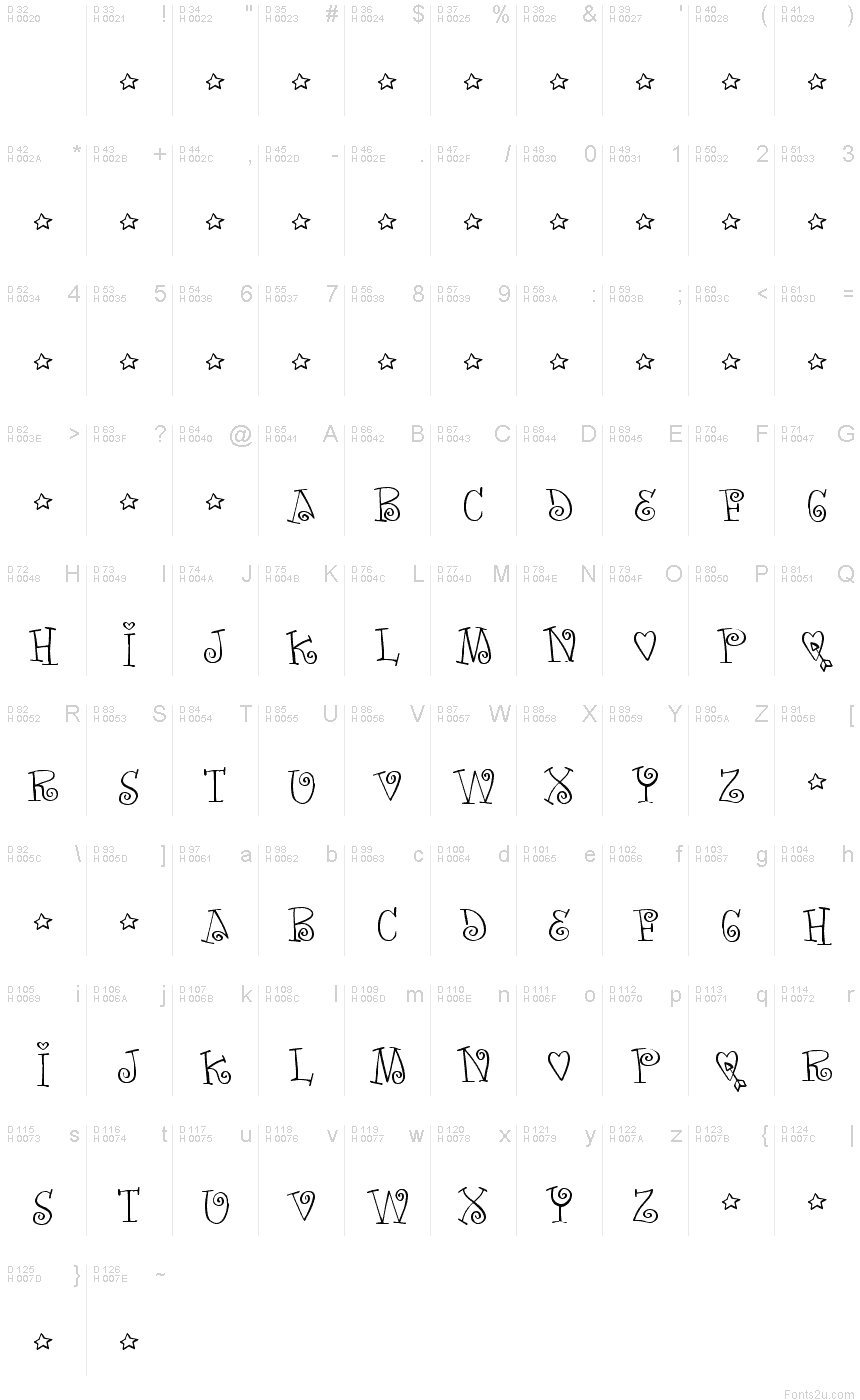
Words of Love autorstwa Jakoba Fischera to darmowy krój displayowy o romantycznym, popowym charakterze, wyglądający jak rysowany odręcznie. Wysokie, smukłe litery układają się w duże, spiralne pętle, a wplecione w zestaw motywy serc nadają krojowi słodkiego, lekko figlarnego uroku – bardziej w klimacie kartki walentynkowej niż formalnego pisma.
Pasuje do radosnych opakowań, zaproszeń na przyjęcia, tytułów w albumach, szyldów kawiarni i zabawnych plakatów, gdzie te otwarte zawijasy potrafią powiedzieć wszystko za pomocą zaledwie kilku słów. Jako darmowy font, sprawdzi się również w nagłówkach, na planszach tytułowych i w krótkich grafikach społecznościowych, którym chcesz nadać domowy, miłosny klimat, unikając przy tym przesadnej sterylności.